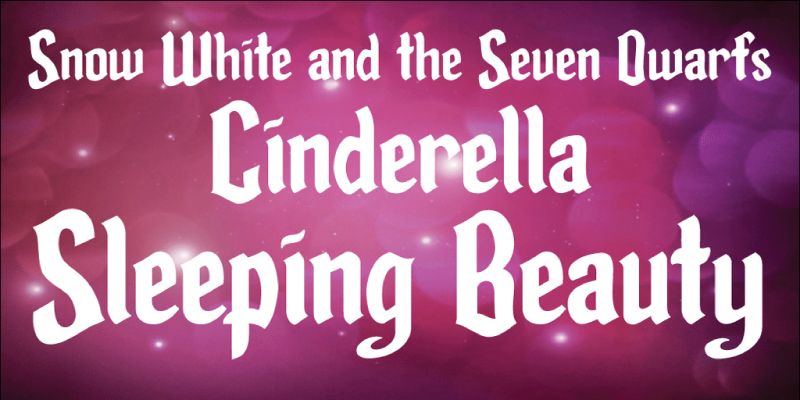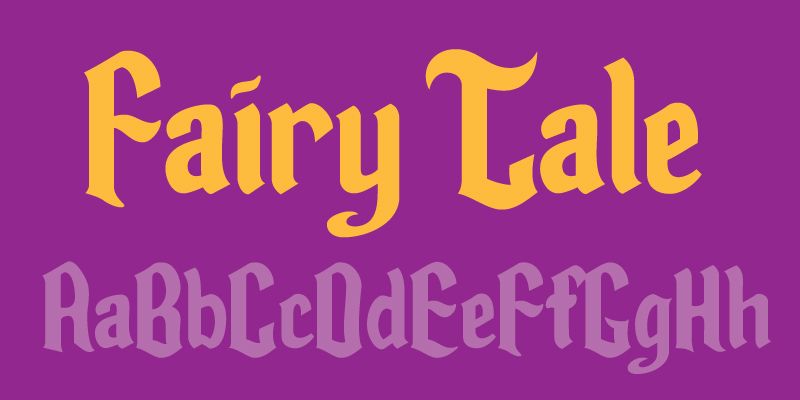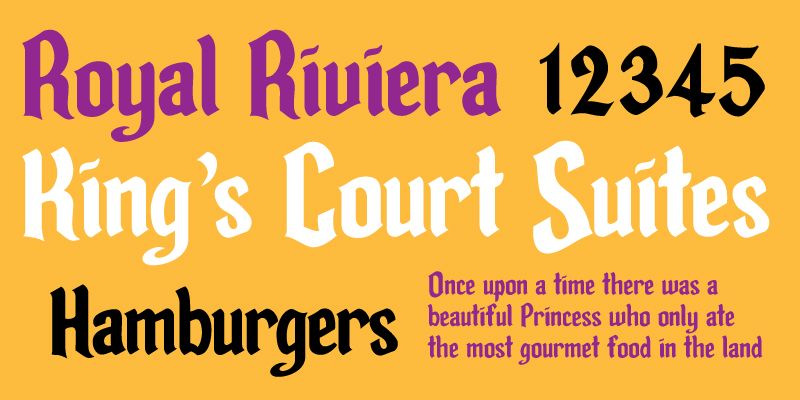
Fairy Tale es una de las primeras fuentes de Jukebox, inspirada en el cartel de una película de animación de los años 50. Captura el encanto del viejo mundo y la sensación de esas historias de la infancia que todos amamos.
Jukebox es obra de Jason Walcott, veterano diseñador de fuentes. Jason diseñó su primer tipo de letra llamado “Holiday Times“ en otoño del 2000 y tras esto emprendió un largo y maravilloso viaje que le llevó a crear la Jukebox que existe hoy.
Después de diseñar otras cinco o seis fuentes, Jason comenzó a vender sus tipografías en MyFonts.com en el verano de 2001. En ese momento, su negocio tipográfico recibió el nombre de “JAW Fonts“. Rápidamente, varios de sus diseños de fuentes se volvieron populares en MyFonts.com y sus ventas aumentaron hasta finales de 2002.
A principios de marzo de 2003, Walcott recibió una llamada telefónica de la entonces prometedora Veer Inc. Veer mostró su interés en gestionar su biblioteca de fuentes, que para entonces incluía unas 50 tipografías. El acuerdo con Veer dio sus frutos y se tradujo en la creación de una asociación empresarial, por lo que JAW Fonts echó el cierre, se sometió a una reestructuración y volvió a nacer como Jukebox en junio de 2003. Este producto exclusivo de Veer entre 2003 y 2015 se convirtió en una de las referencias del sector en bibliotecas de estilos de fuentes disponibles. Las fuentes de Jukebox han sido utilizadas en innumerables productos y diseños, películas, libros, producciones de televisión y demás por empresas como Disney, HGTV, The Food Network, Parques Temáticos Disney, Hershey’s, VistaPrint y muchos otras. En 2011, la familia de fuentes Eloquent de Jason se hizo un hueco en la lista de “Mejores diseños de tipografía“ que aparece en la edición anual de tipografía de la revista Communications Arts.
El 31 de marzo de 2016, Veer cerró sus puertas para siempre y la conservación de la biblioteca de Jukebox pasó a manos de Jason, quien se comprometió a garantizar que Jukebox siguiera aportando al mundo del diseño tipografías profesionales de alta calidad.